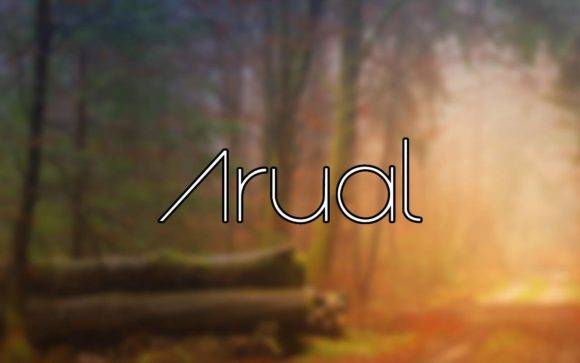
Arual é uma fonte deslumbrante, bela e fluida que dá vida aos seus designs. Com seus caracteres bem equilibrados, ela se adapta a uma ampla gama de projetos, desde design gráfico até arte digital. Seja para criar um logotipo, um pôster ou um design web, a fonte Arual adiciona elegância e criatividade. Baixe-a gratuitamente e dê vida às suas ideias mais imaginativas.